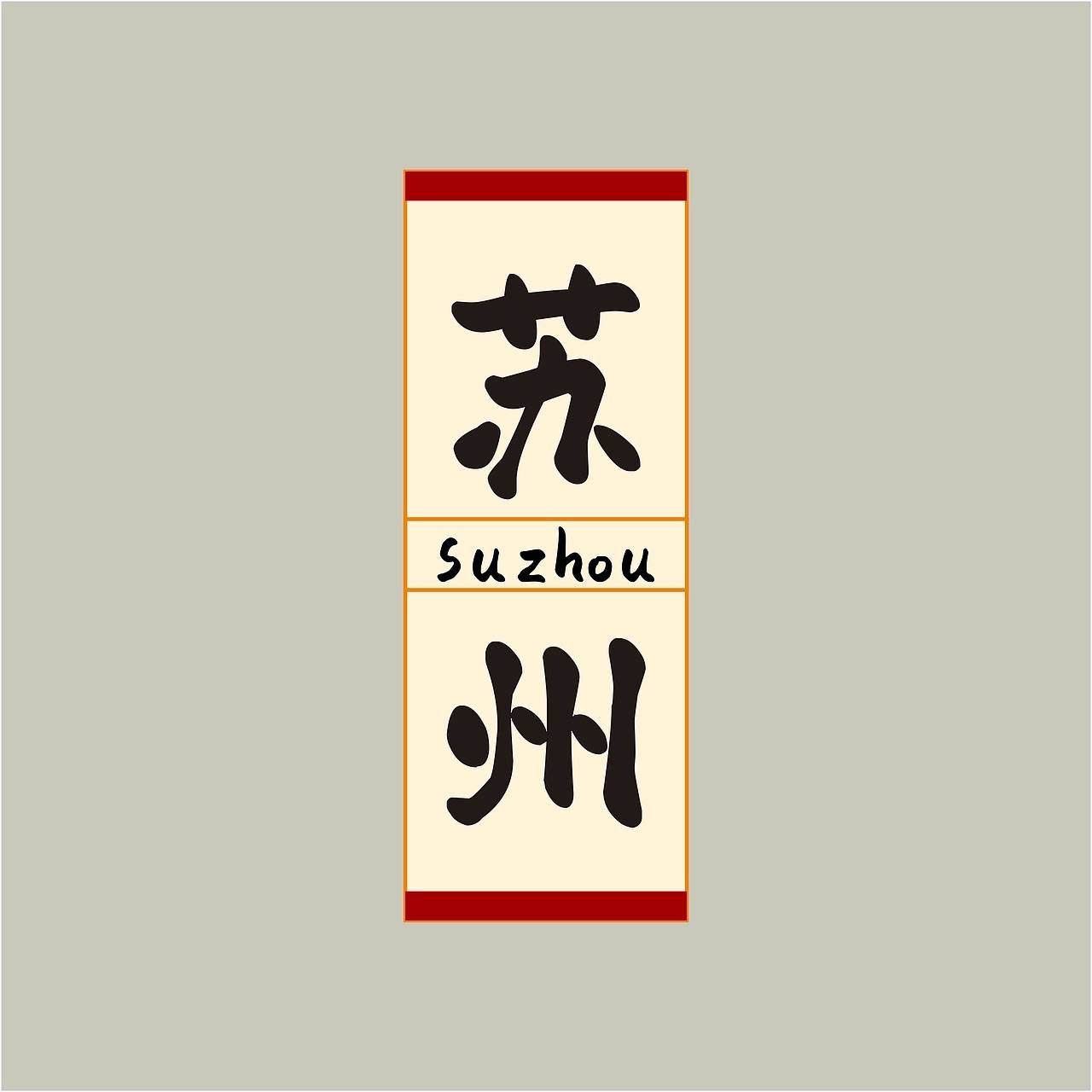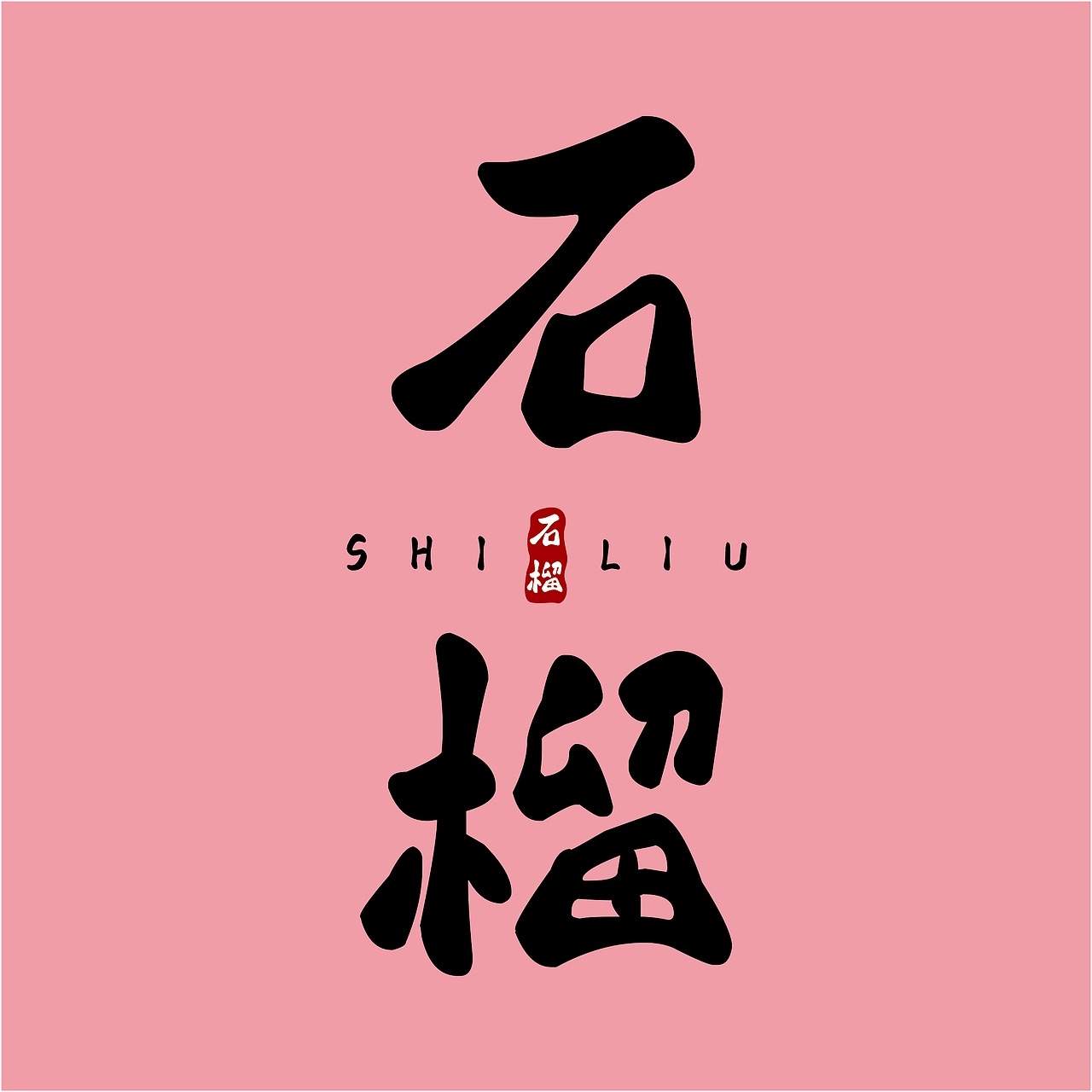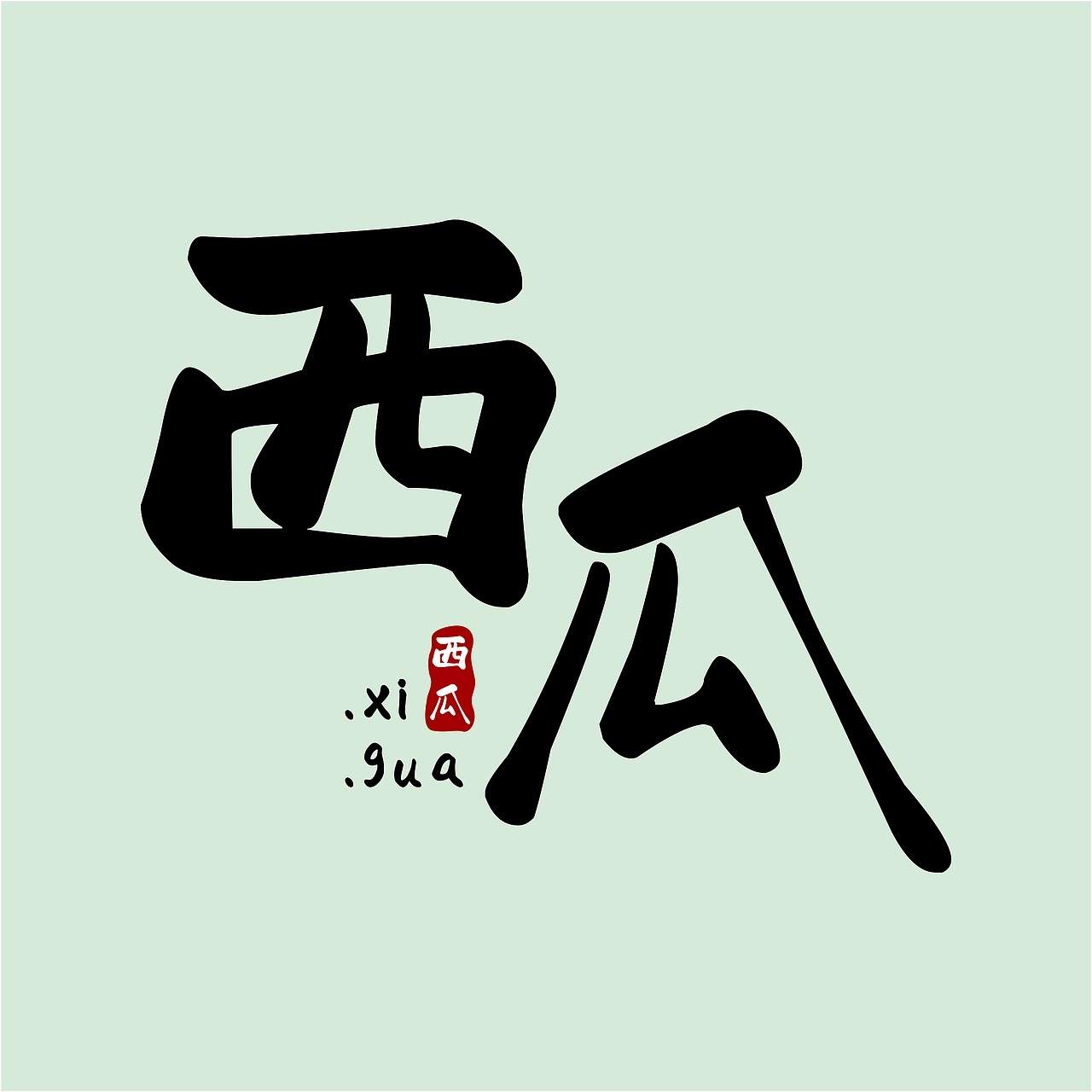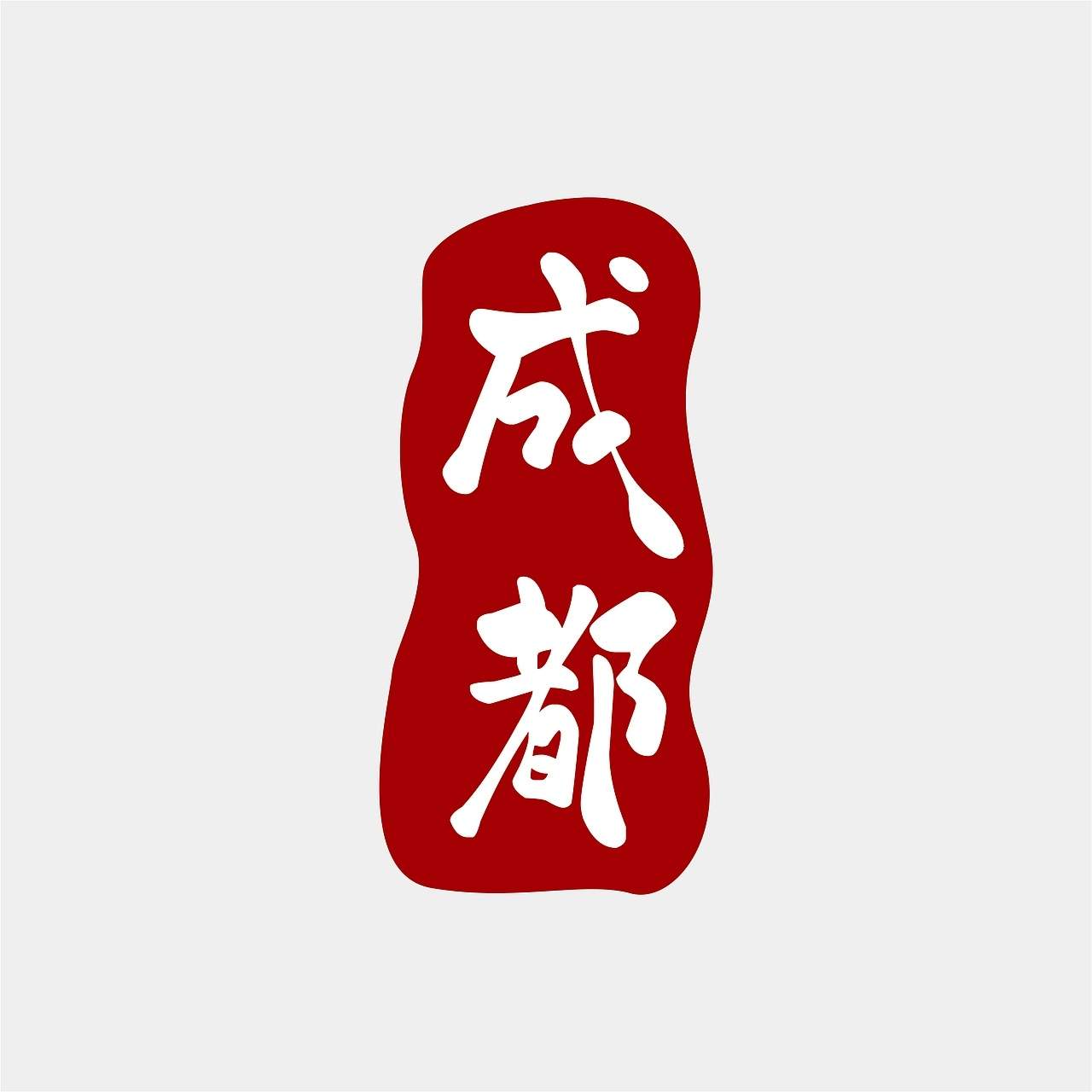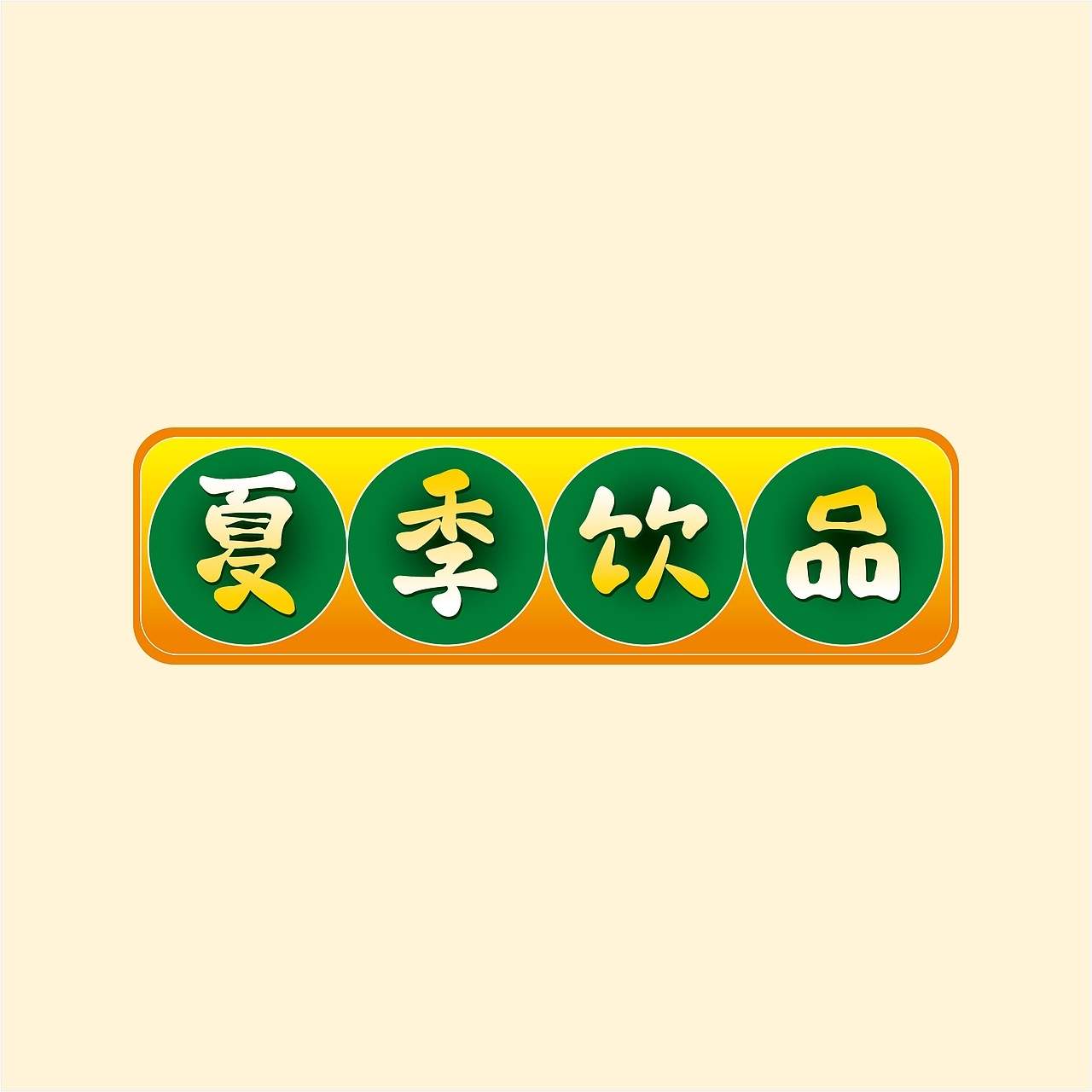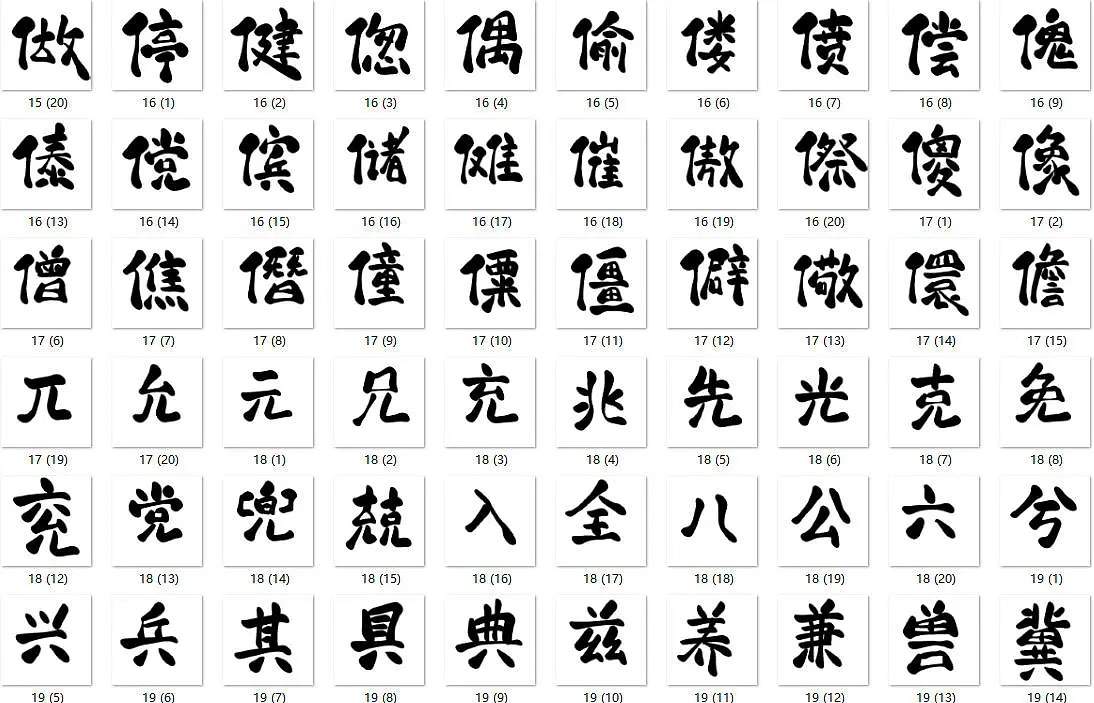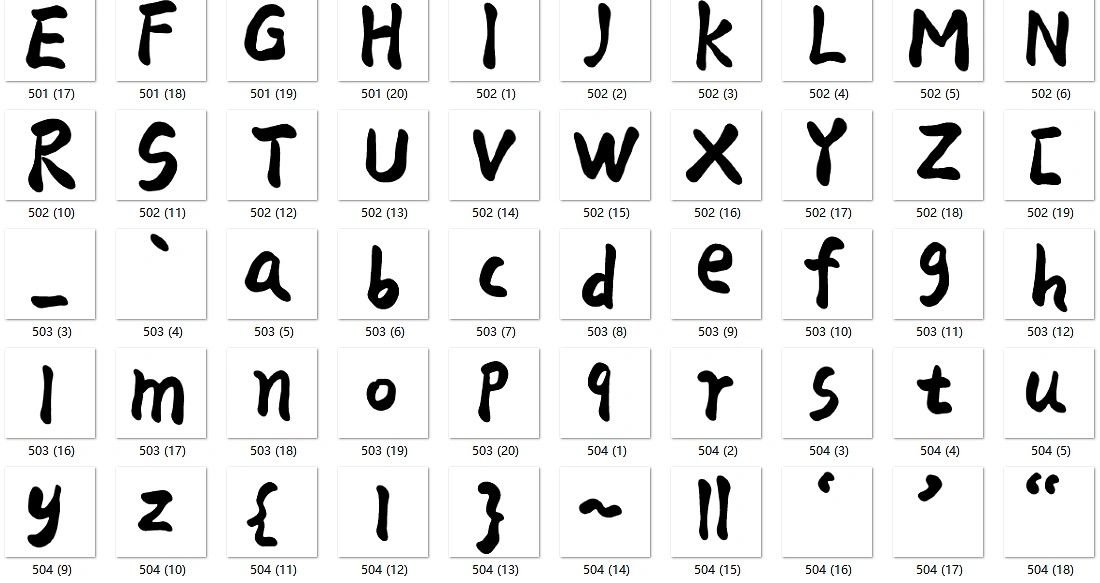
此款字体「赖江湖墨暖圆书」,全程平板手绘独立创作,全套独自完成。
整体是柔和圆润的平板手写风格,边角全部做圆角处理,弱化尖锐笔触,自带松弛的卡通氛围感,手写自然不潦草,大小字号都好驾驭。
名称:赖江湖墨暖圆书
风格:平板手写 / 圆润卡通
适用:短视频字幕、海报标题、儿童文创、包装文案、手账、电商排版、PPT、门店标语